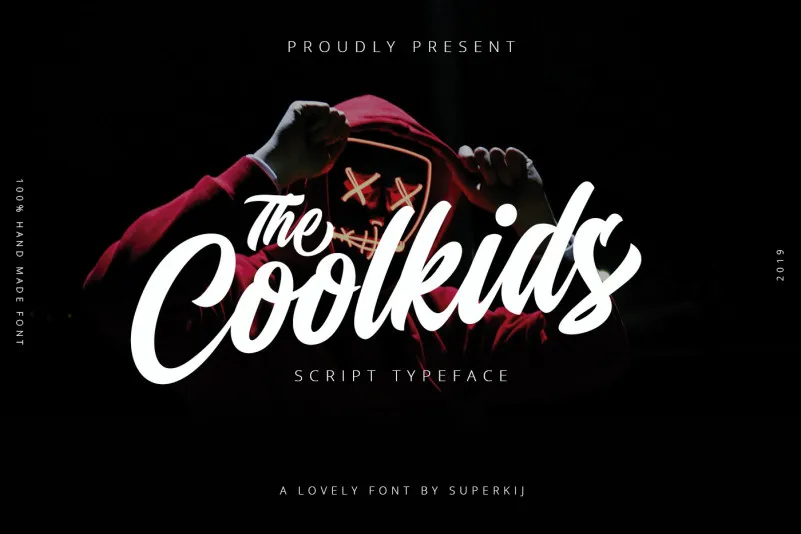
Coolkids Script Font – Download Grátis
Estou aqui uma nova fonte de escrita script para você. Introduzimos a Coolkids Script Font, uma opção perfeita para qualquer necessidade que precise de uma tipografia elegante e vibrante. Desenhada pelo designer Adhi Nugraha da superkij, esta fonte do tipo é ideal para uso em projetos de título ou qualquer outro design onde um estilo sofisticado seja desejado. Com seus traços sólidos e linhas leves, Coolkids Script Font é uma escolha perfeita para criar mensagens com profundidade e charme. Adaptable e poderosa ao mesmo tempo, esta fonte é a solução ideal para qualquer projeto que exija um design de escrita script incrivelmente único. Seja você um designer gráfico ou criativo, Coolkids Script Font é uma ótima adição à sua coleção de recursos de design. Aproveite o equilíbrio elegante desta fonte e deixe seu trabalho em destaque com estilo e sofisticação.